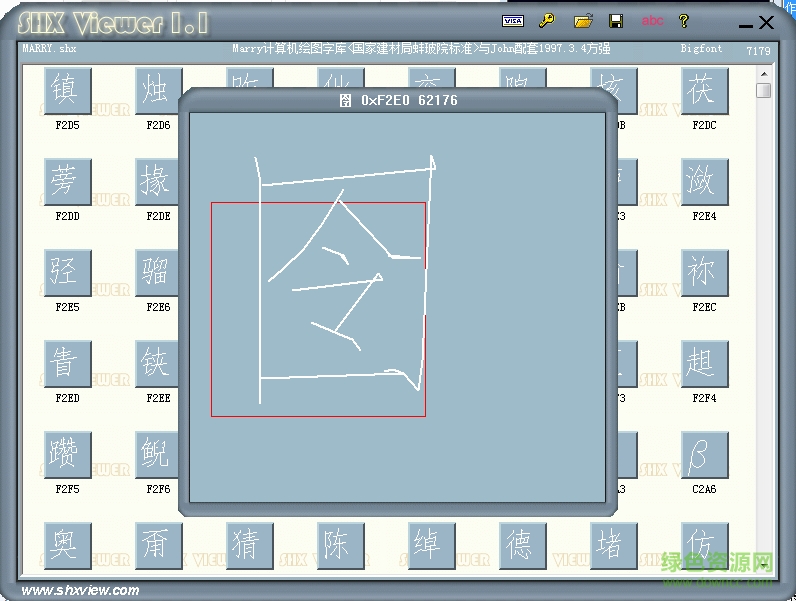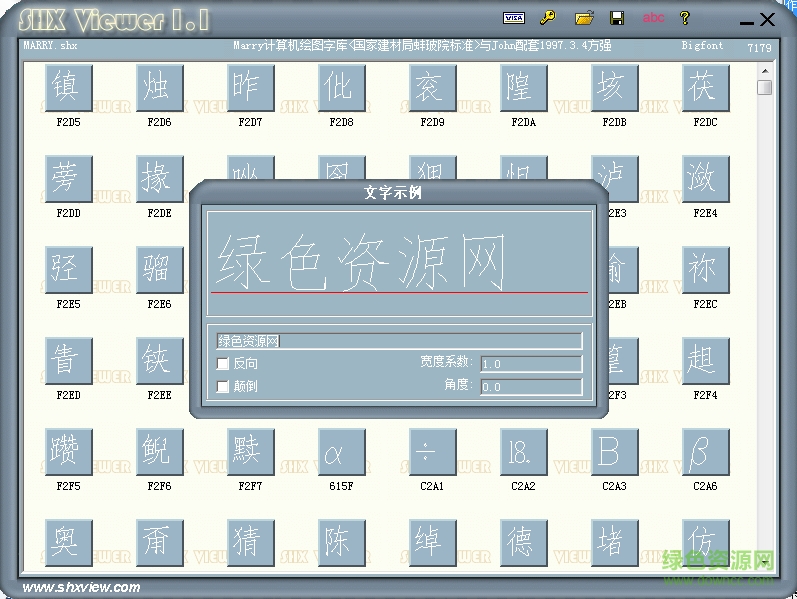
marry.shx是計(jì)算機(jī)繪圖字庫中一款中文字體,不支持英文輸入,有著纖細(xì)的線條和流暢的字形,讓你的名片設(shè)計(jì)、工程繪圖更加有創(chuàng)意性,綠色資源網(wǎng)提供免費(fèi)下載服務(wù)!
marry.shx是符合國家建材局蚌玻院標(biāo)準(zhǔn)的中文字體,與john配套,支持中文和字符,不支持英文字母,字體簡潔好看,歡迎使用!